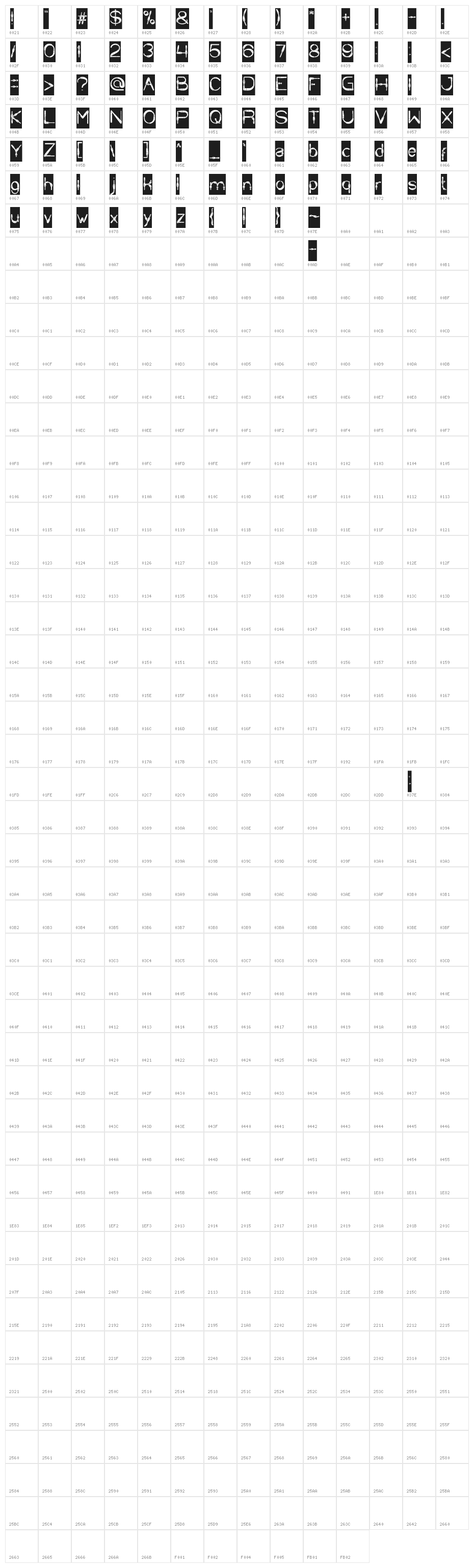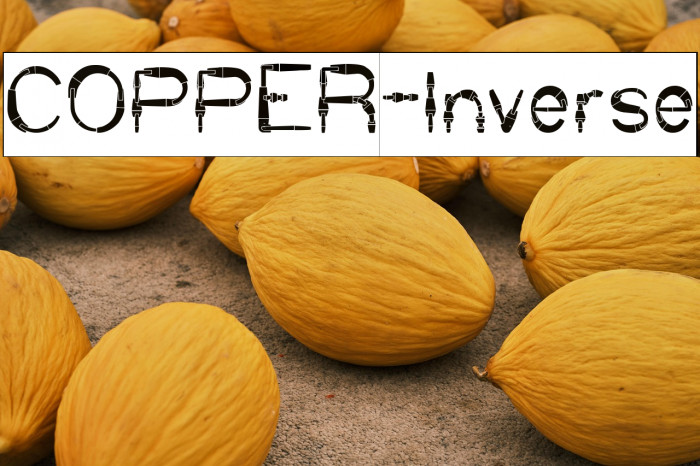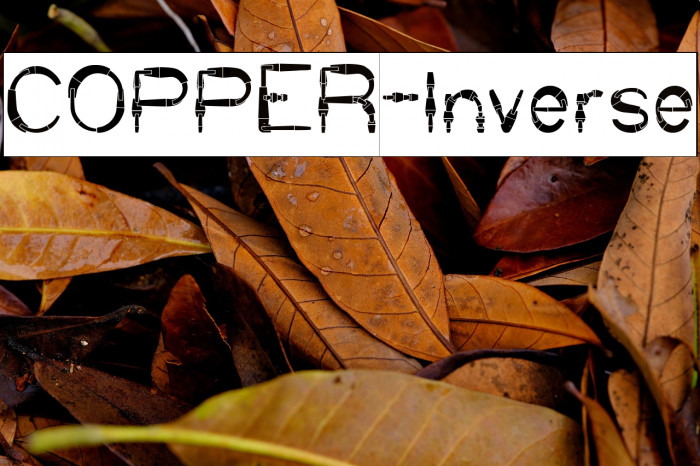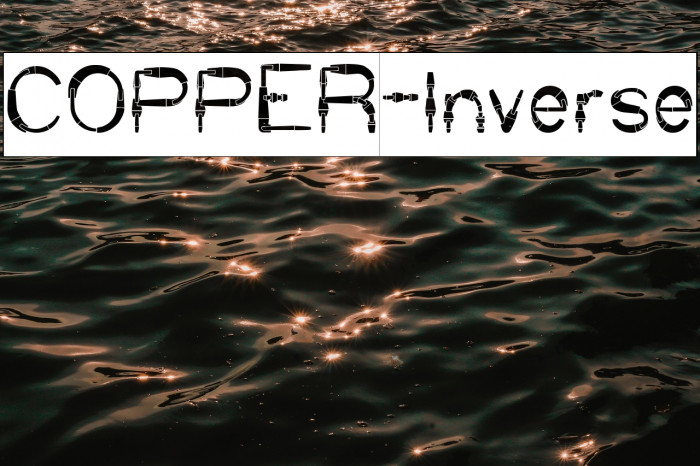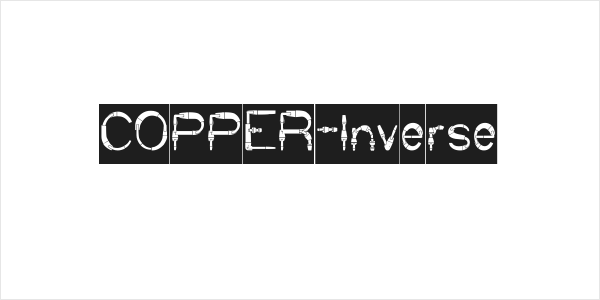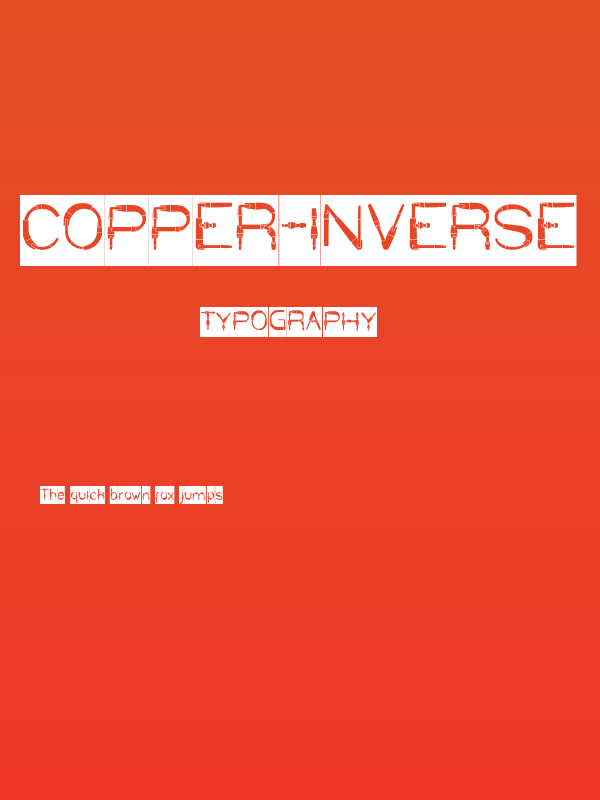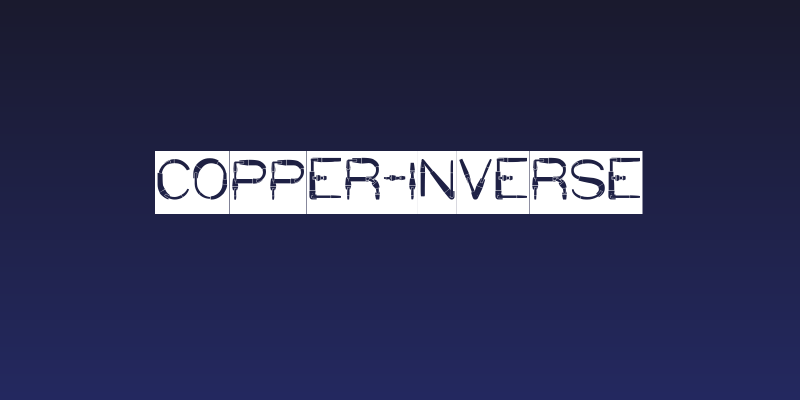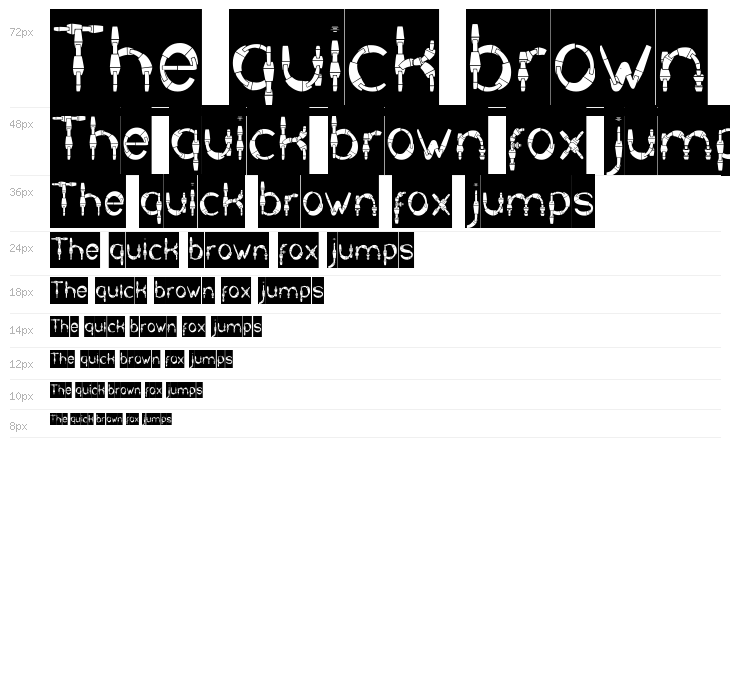
COPPER-Inverse Font
| 整体风格 | Industrial, Mechanical |
| 使用场景 | Logos, Posters, Display text |
| 推荐项目 | Ideal for projects related to engineering, technology, or industrial design. Suitable for creating logos, posters, or any graphic design work that requires a mechanical or technical aesthetic. |